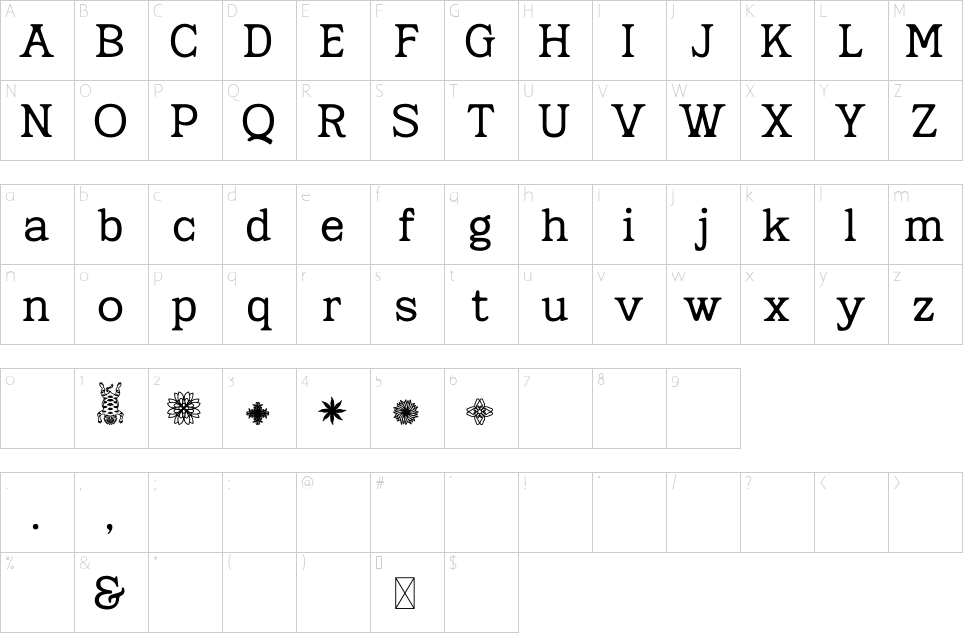
A fonte Marzena oferece um estilo elegante e versátil para design gráfico, ideal para criações tanto profissionais quanto pessoais. Desenhada pela equipe da HisHand Studio, a Marzena foi projetada para oferecer uma variedade de usos, desde títulos até detalhes de texto, garantindo uma aparência atraente e sofisticada. Com seu design cuidadosamente cuidado, a Marzena se destaca como uma escolha ideal para qualquer projeto que deseje transmitir uma sensação de sofisticação e elegância. Para quem busca uma fonte grata e de alta qualidade, a Marzena é uma ótima escolha. Em 2023, ela foi baixada 313 vezes, evidenciando sua popularidade e valor. Se você está procurando por uma fonte que se destaca e oferece uma maneira elegante de personalizar seu design, Marzena é uma fonte que você não pode deixar de experimentar.